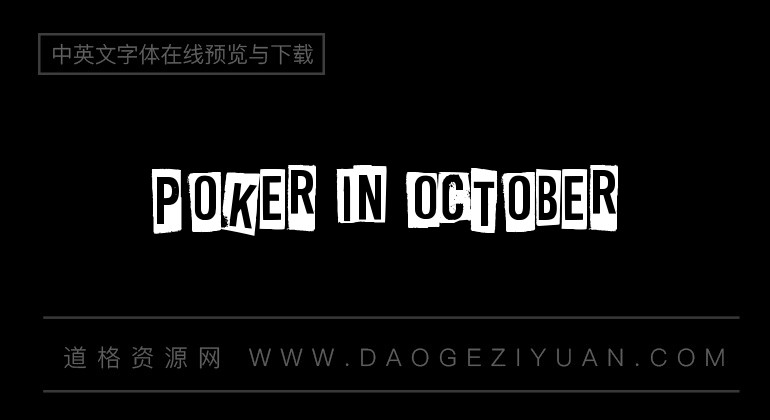
? Poker In October 字体是一款拥有独特设计风格的字体,它具有清新、活泼、简约的特点。它的字体设计灵感来源于十月的秋天,以及每年十月的世界扑克日,展现出淡雅、温柔、活力十足的设计风格。Poker In October 字体的设计灵感源于扑克牌,主要特点是简单、清新、活泼、精致。它可以用于广告、海报、标志等平面设计,也可以用于网页设计和网站开发。内容介绍
Poker In October是一款非常不错的手写艺术字体,具有很好的视觉感,适合于文化类的宣传设计、商业类品牌的广告和产品包装设计以及个性化文字排版等较多场景。